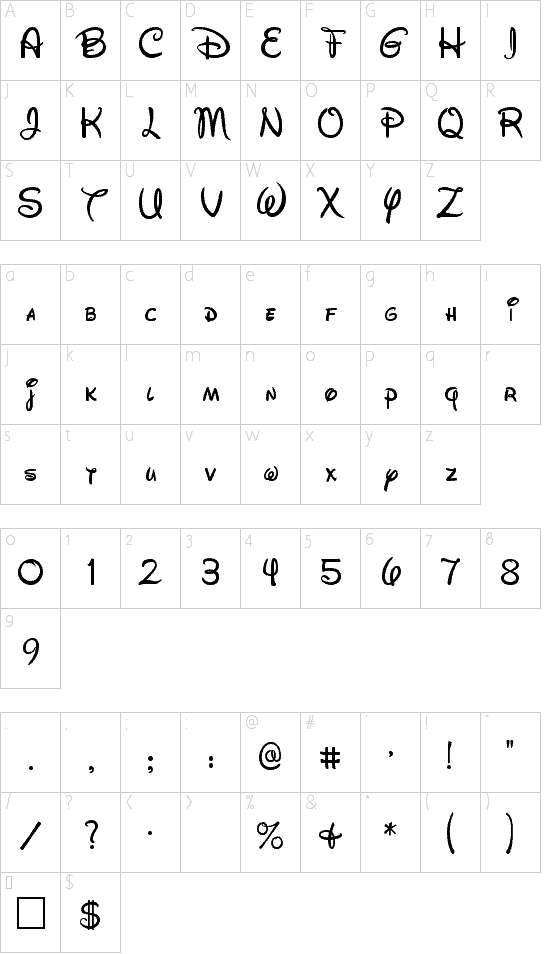
Se sei un appassionato del mondo Disney, avrai sicuramente notato l’iconico stile del font Walt Disney utilizzato in vari loghi, film e merchandising della Walt Disney Company è una delle più importanti aziende del mondo, operativa nel settore dell’entertainment ed in particolare nelle produzioni cinematografiche e televisive.
Questo carattere tipografico è diventato uno dei simboli distintivi del brand, richiamando subito alla mente l’immaginario magico e creativo che accompagna ogni produzione Disney dagli anni ’20 ad oggi. Anche il logo del canale di streaming Disney+ è creato con lo stile di questo carattere tipografico.
La storia del Font Walt Disney
Il logo della Walt Disney Company riprende lo stile della firma del fondatore della compagna, Walter Elias Disney, notissimo imprenditore, animatore e regista cinematografico di opere indelebili come Fantasia e Cenerentola.
Si tratta di una scrittura che è stata stilizzata nel tempo per diventare un simbolo riconoscibile globalmente. Anche se non esiste un vero e proprio font ufficiale rilasciato dalla Disney, diversi designer hanno creato versioni che si ispirano a questo stile, permettendo a fan e creativi di utilizzarlo nei propri progetti.
Il font è caratterizzato da linee eleganti, morbide e allo stesso tempo giocose, che rispecchiano perfettamente il mondo magico creato dalla mente geniale di Walt Disney. I caratteri distintivi di questo font sono le iniziali “W” e “D” era “i” minuscola con il suo iconico pallino.
Il Font Walt Disney Script
Il font Walt Disney Script è un font gratuito, non ufficiale, che riproduce fedelmente lo stile dell’inconfondibile scritta Walt Disney.
L’autore del font è Robert Johnson che non è collegato in alcun modo alla The Walt Disney Company.